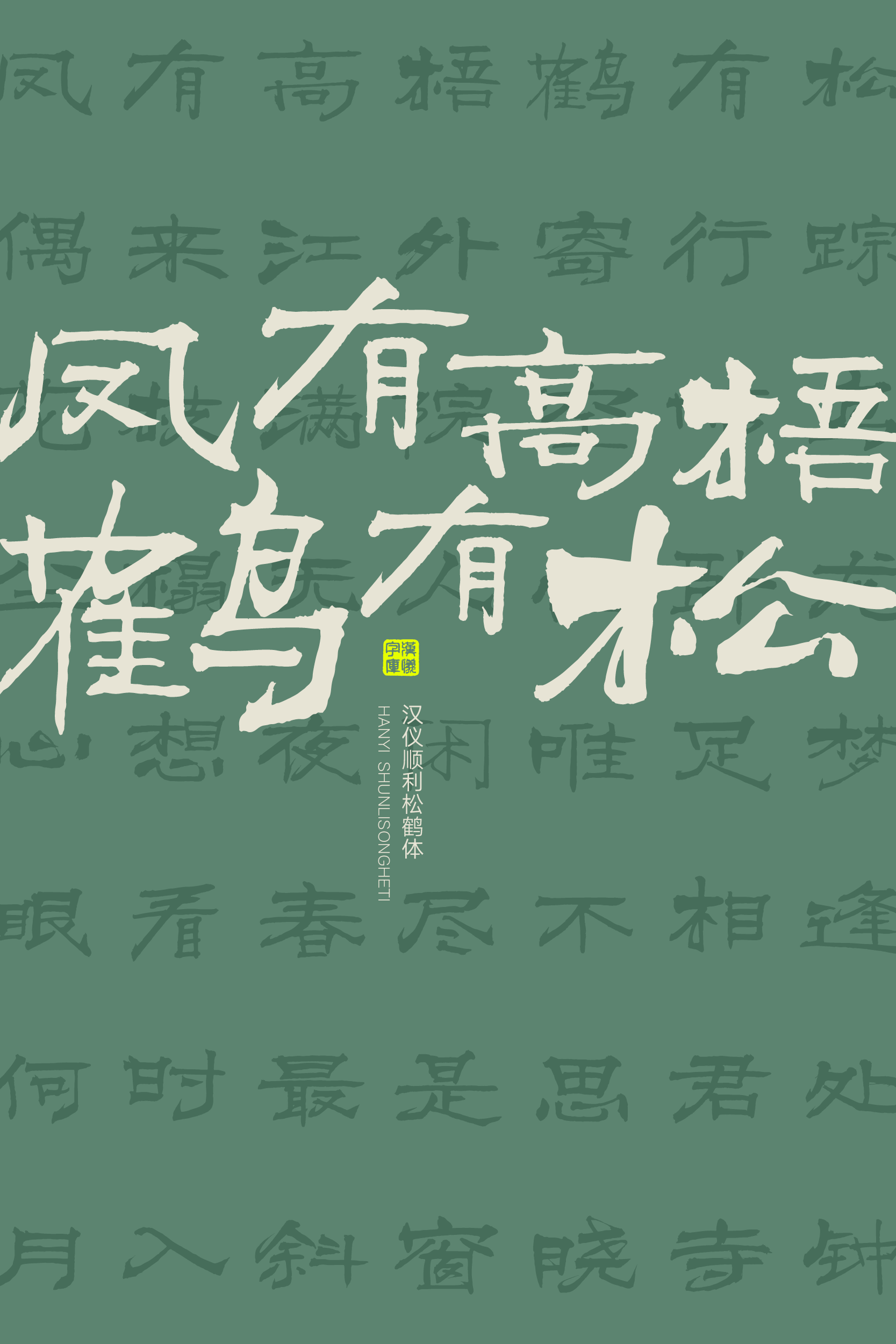
一款自带“武功”的字体
汉仪顺利松鹤体|金石篆刻的现代隶书
汉仪签约作者范顺利书写的汉仪顺利松鹤体,松形鹤骨,器宇不凡,是一款极具个性的书写字体,结合了隶书风格和金石刀笔的特点。落笔凌厉、笔锋苍劲,整体行气通畅,气韵生动,显露潇洒的精神气质。这款字体适合书籍画册、展览海报、产品包装等多种使用场景,作为标题字体或较短文本的排版,渲染东方意境的同时彰显个性。
汉仪顺利松鹤体|作者介绍
范顺利,黑龙江鹤岗人,现居杭州,
汉仪字库签约作者、阿里巴巴创意设计专家、奥运火炬飞扬字体设计师、阿里巴巴新六脉品牌字作者、达摩院品牌字作者、寻味中国年联合发起人、顺利物语文化创意负责人。
顺利的书法风格集合金石篆刻和隶书苍劲的特点,又保有文人的内敛特质,大胆的将传统书法的精髓与现代设计相结合,突破创新。
(顺利为亲友篆刻题字)
汉仪顺利松鹤体|字体特征
松针苍劲留其形,鹤鸣高岗品其声。汉仪顺利松鹤体最大的特点就是笔锋凌厉、结构设计舒展,能感受到侠客剑气和文人风骨的结合。
(汉仪顺利松鹤体手稿)
在书写的时候,笔画疾速变化,在平稳的结构中建立起整体的行气平衡。
字形取横势,重心居中,舒展而自由。笔画如松竹般稳定。
整体笔画风格清癯而苍劲,间有粗厚笔画和浑圆笔画。平直笔画纤直、稳定,收笔或圆润或凌厉,撇捺收笔迅速回勾。
笔画时而疾速灵动,连带勾连如刀剑飞舞。时而悠然平衡,沉静稳定如萧笛声声。
汉仪顺利松鹤体在书写笔法上结合了金石刀笔的特点,是整体风格具有峻劲的特征。
(寿山石“金石千秋”章 钤本,故宫博物院藏)
历史悠久的金石学,以及清末民国时期盛行的碑学,造就了自清末至当代中国的文字设计实践中对于金石趣味的审美。从晚清康有为所创刊物的刊名字体,到钱君匋、鲁迅、闻一多等人的书籍封面设计,再到中国现代公共领域的设计,都可见金石趣味的普遍存在。
参考资料:周博,《中国现代文字设计图史》(北京大学出版社,2018),136-140
汉仪顺利松鹤体|中西文匹配
汉仪顺利松鹤体的西文部分延续了中文部分的横向舒展的走势和苍劲的凌厉笔法,在西文字形中也能感受到东方意蕴。
汉仪顺利松鹤体|排版应用
汉仪顺利松鹤体在精神表现上融合了多重东方气质,既有文人墨客的超凡脱俗,也有江湖游侠的豪情逸致,又洋溢着潇洒的个性。
汉仪顺利松鹤体|字体样张